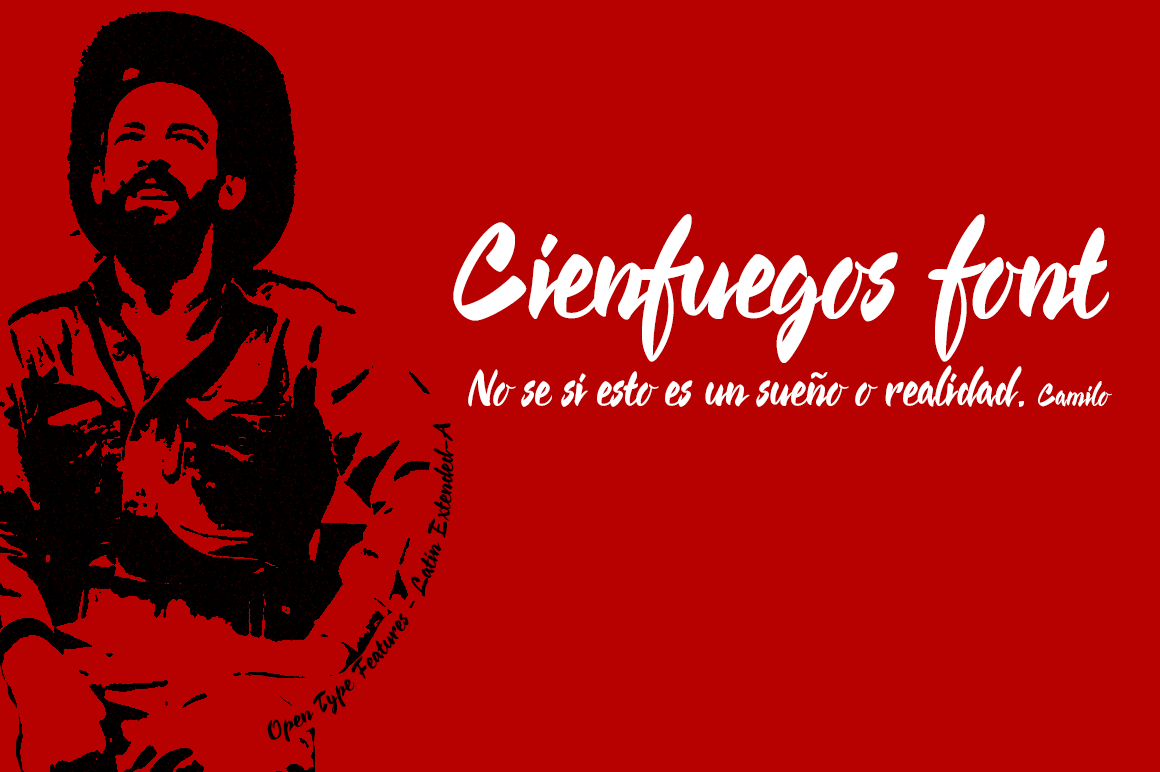
Cienfuegos font
A Cienfuegos é uma tipografia escrita a mão concatenada dedicada ao revolucionário cubano Camilo Cienfuegos, um humanista que cresceu sob a liberdade de dois anarquistas espanhóis como pais. Inspirado no nome de sua fonte e em memória de suas raízes libertárias, esta tipografia não apenas reflete a essência da história do revolucionário Cienfuegos, mas também incorpora simbolismos que remetem à comunidade anarquista. O símbolo de Bitcoin (ligaturas) integradas na fonte é um elemento interessante e único que proporciona uma conexão entre o passado libertário da Cuba e as tecnologias modernas. Com foco em seu uso exclusivo pessoal, a Cienfuegos oferece uma versão completa para download com licença comercial, permitindo aos designers e profissionais de gráficos explorarem este rico conjunto de letras. Para aqueles interessados em usar esta font de forma pessoal ou não-comercial, ela está disponível gratuitamente; enquanto os usuários que desejam incorporar a Cienfuegos em seu trabalho para fins comerciais precisam adquirir uma licença comercial.